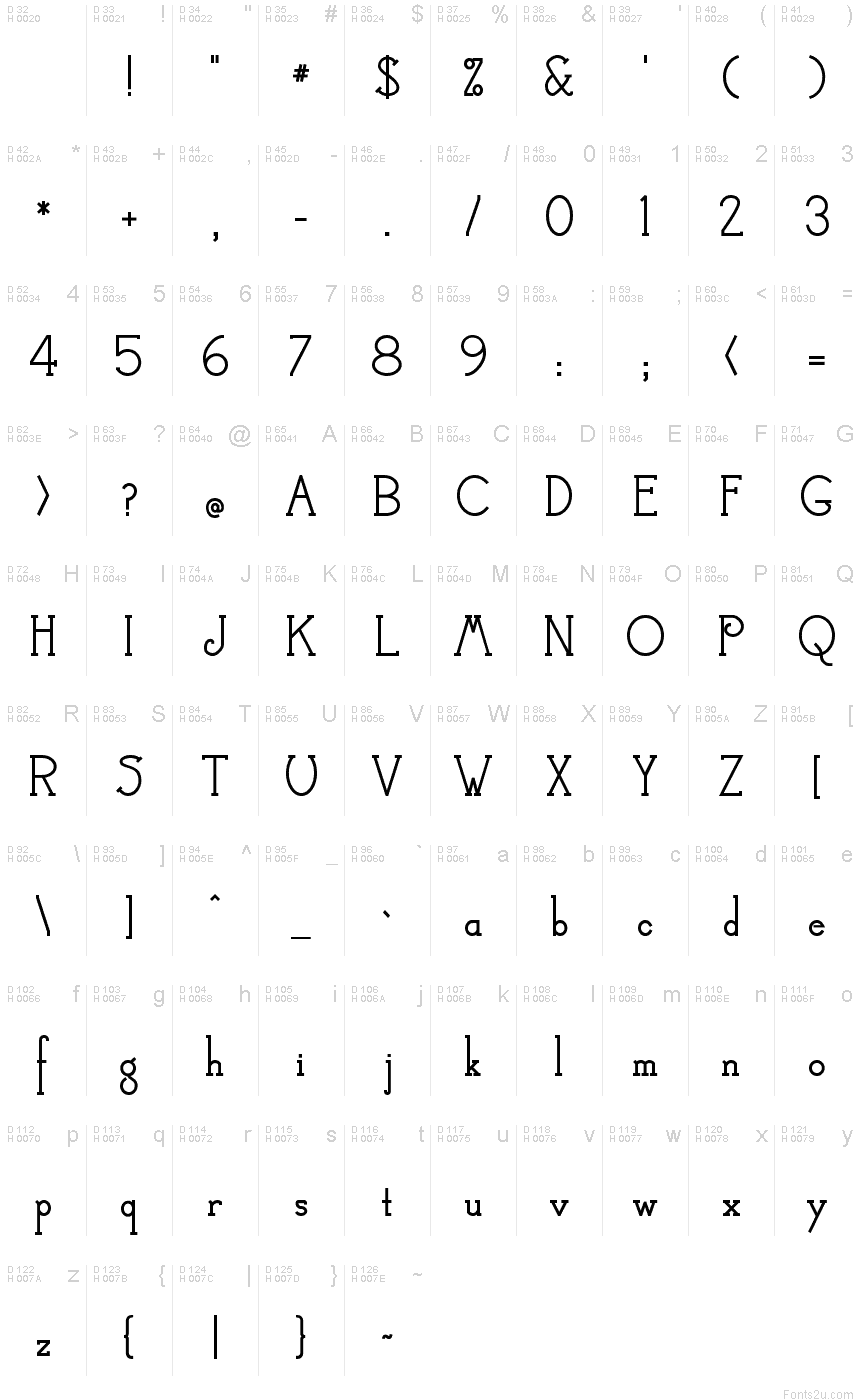
Camelot MF Bold autorstwa Ricka W. Muellera to darmowy krój pisma typu display w stylu retro, który wygląda, jakby przeniósł się prosto ze starego afisza teatralnego. Wysokie, przypominające różdżki pionowe kreski oraz okrągłe, otwarte obłości tworzą zabawne napięcie między elegancją a ekscentrycznością, a ostre, namiotowe kapitałki dodają szczypty dramatyzmu. Litery wydają się przewiewne i wyprostowane, nadając nagłówkom pełną gracji, nieco kapryśną postawę, która wyróżnia się, nie narzucając się przy tym.
Dzięki Camelot MF Bold zyskujesz wyrazisty głos, który świetnie sprawdza się na plakatach vintage, okładkach książek, w identyfikacji wizualnej butików, menu kawiarnianych, zaproszeniach na wydarzenia i teatralnych tytułach. Odstępy są naturalnie hojne, więc ten darmowy font najlepiej prezentuje się w dużych rozmiarach, gdzie jego nietuzinkowe sylwetki mogą odetchnąć. Połącz go z prostym geometrycznym bezszeryfowym krojem w tekście głównym, aby zachować czytelność, pozwalając Camelot MF Bold nadać całości charakteru.